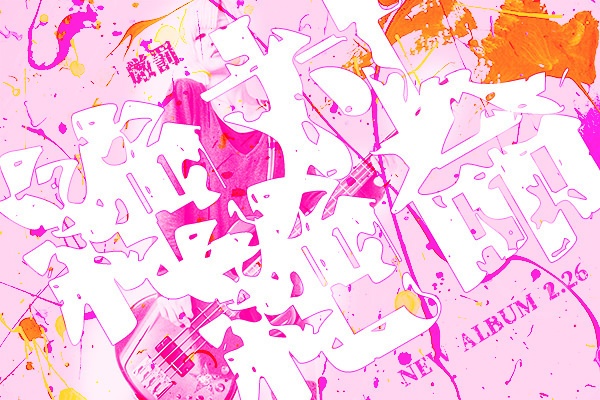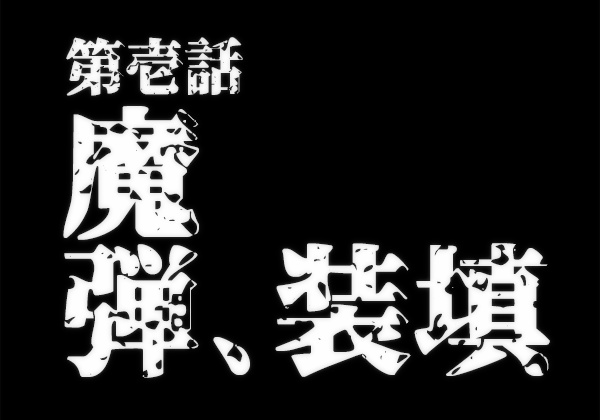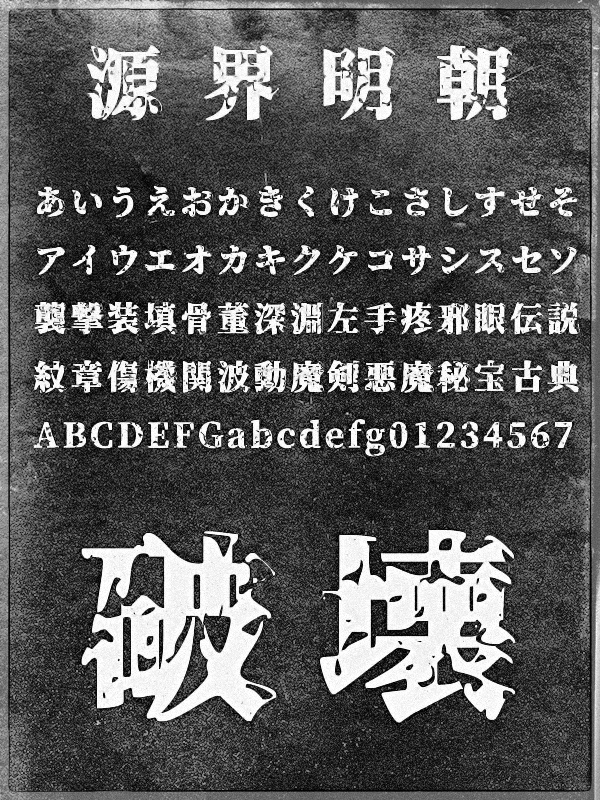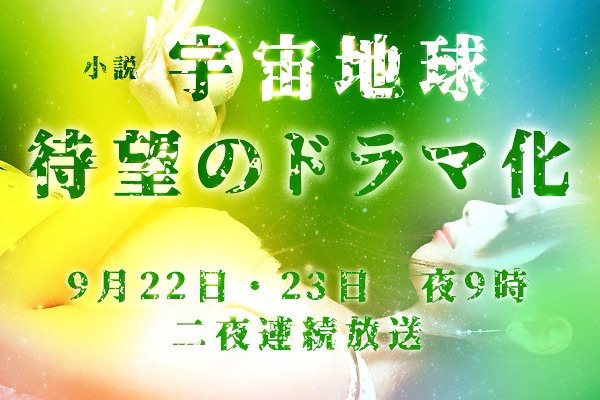
フリーフォント源界明朝
源界明朝 ■フリーフォント使用に当たって フォントをインストールして頂くとパソコンのワープロ、グラフィックソフトなどのアプリケーションを使って自由にデザイン、印刷することができます。個人利用・商用利用にかかわらず、無償で使用することができます。当フォントはSIL Open Font License 1.1のオープンソースライセンスに準じます。 ■源界明朝の概要 源界明朝は以下の派生フォントです。 「源ノ明朝 (Source Han Serif)」 ■書体コンセプト 読める限界ギリギリまで破壊された世界観の見出し向け明朝体にいたしました。 ⚠️このフォントは自由に動画に使えるフォントです。ご利用の際は次のクレジットを入れていただけると、ものすごーく喜びます! –––––––––––––––––––––––––––––– フォント:源界明朝 フリーダウンロード:https://booth.pm/ja/items/1028548 –––––––––––––––––––––––––––––– お好きなSNSをフォローしてください。 Instagram ▶ https://www.instagram.com/flopdesign.font X ▶ https://twitter.com/flopdesign Threads ▶ https://www.threads.net/@flopdesign.font